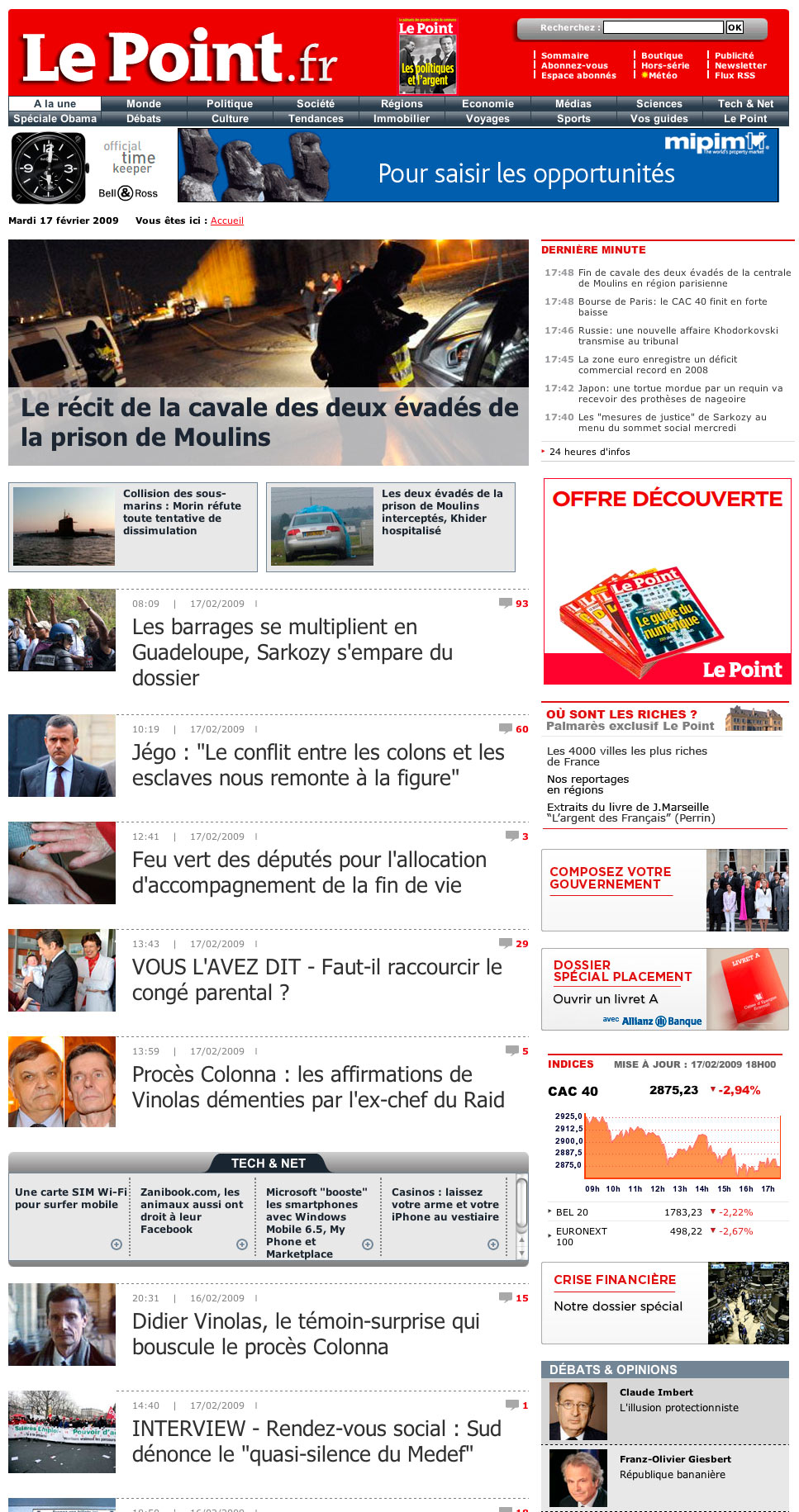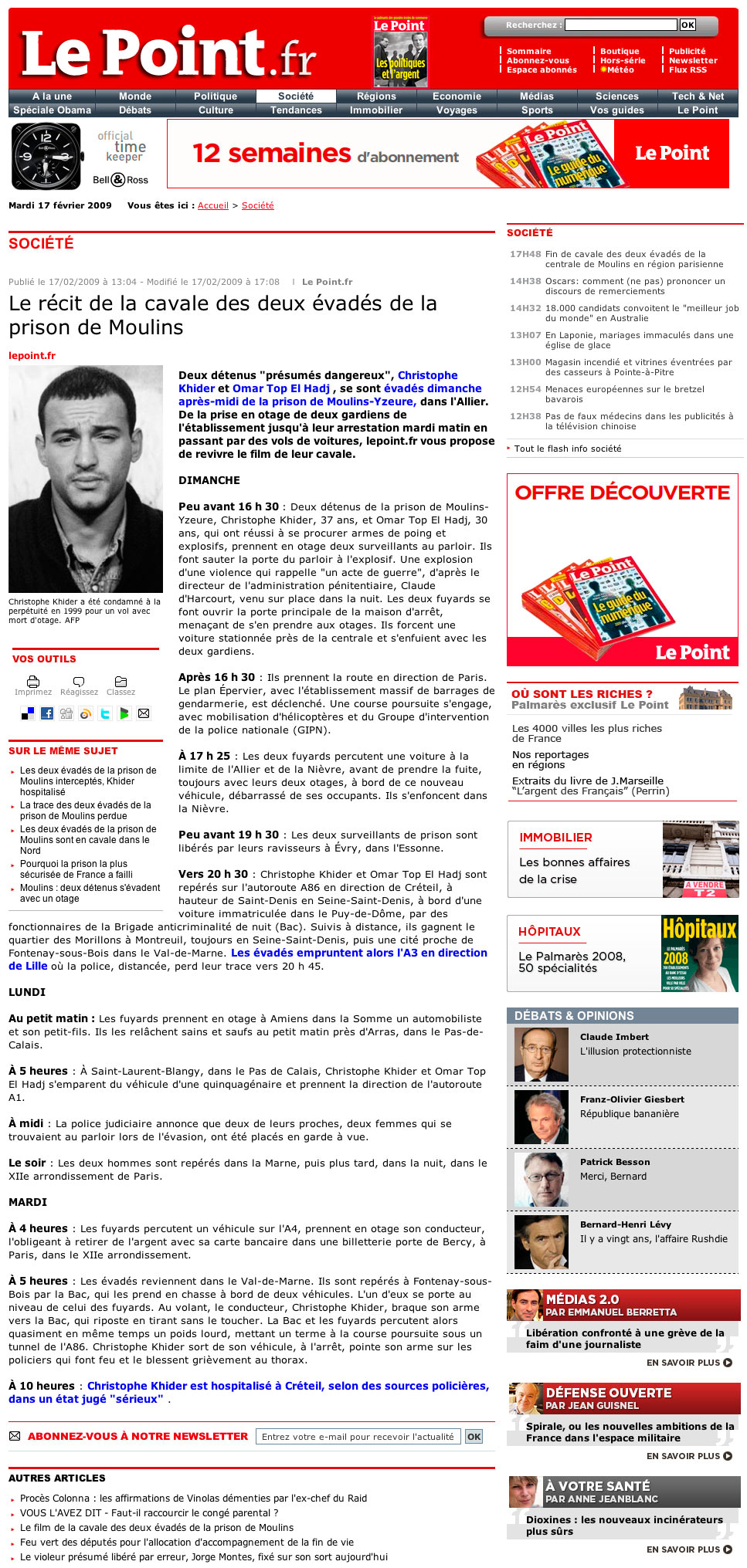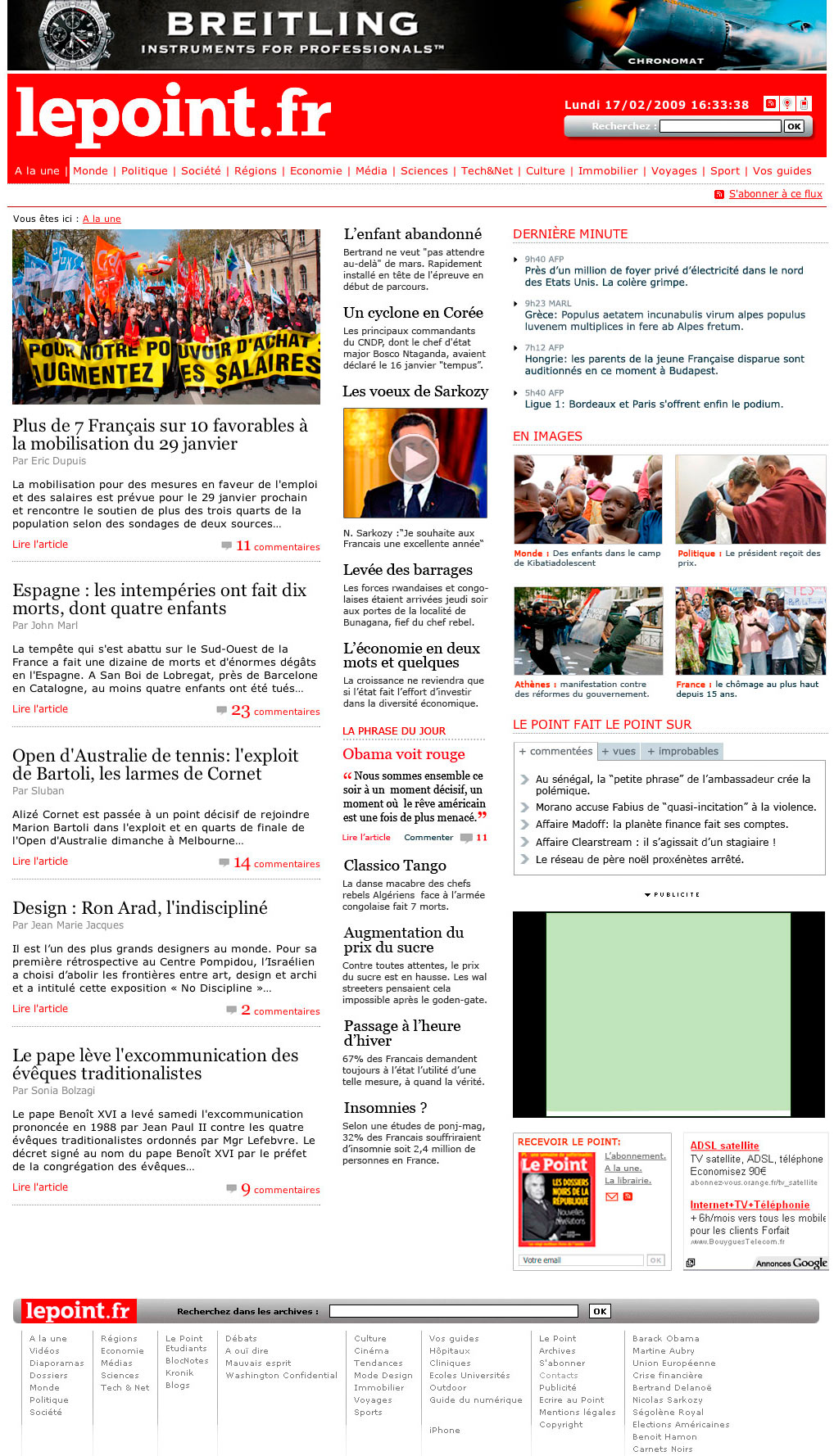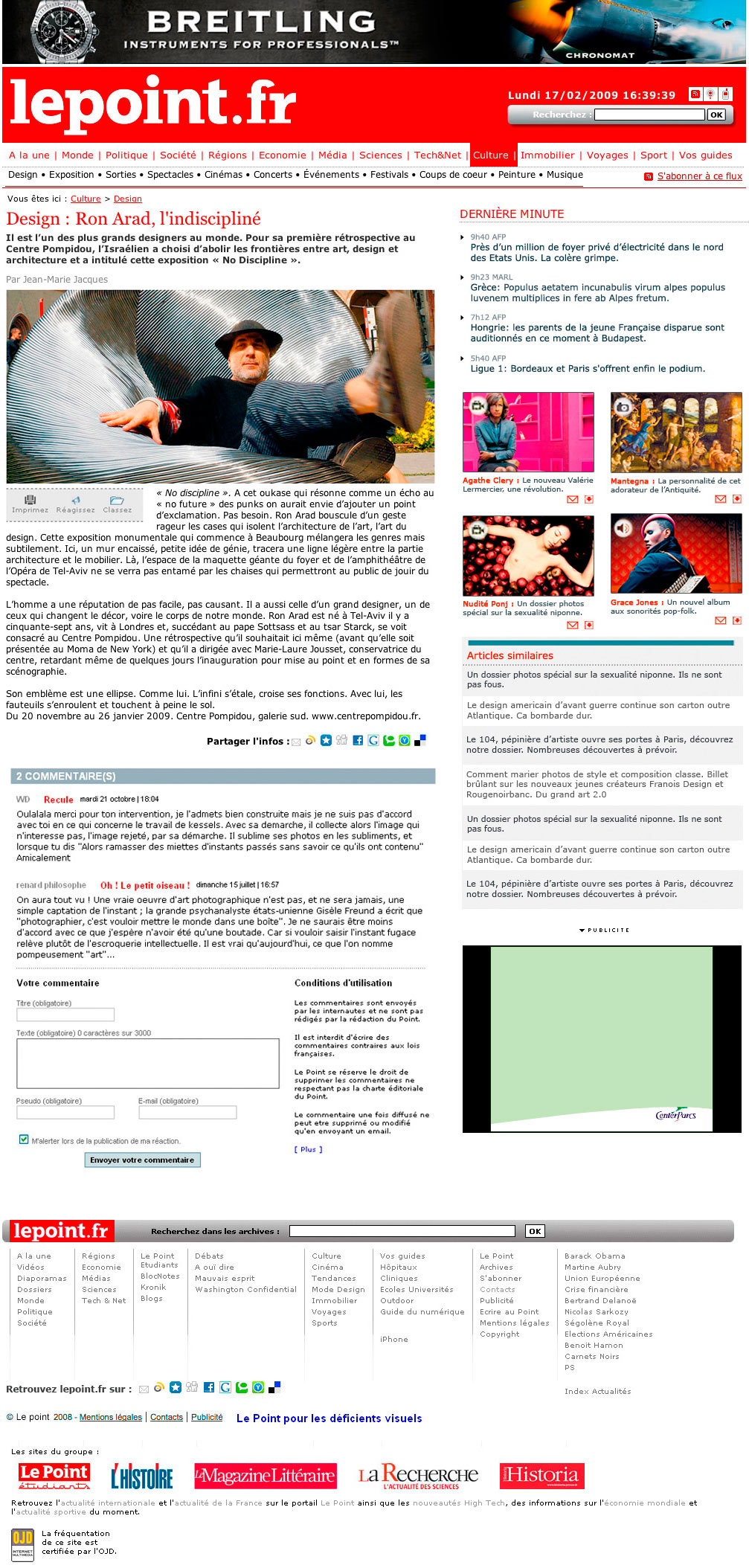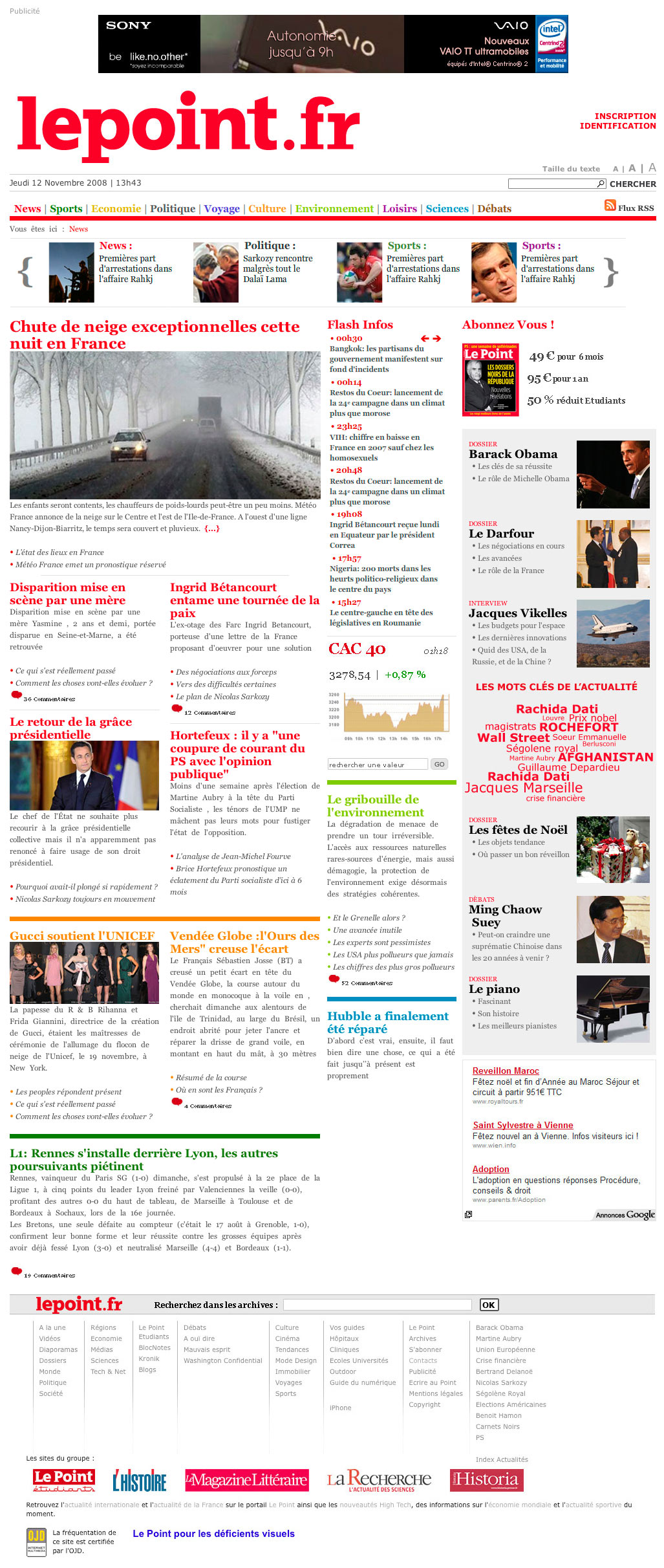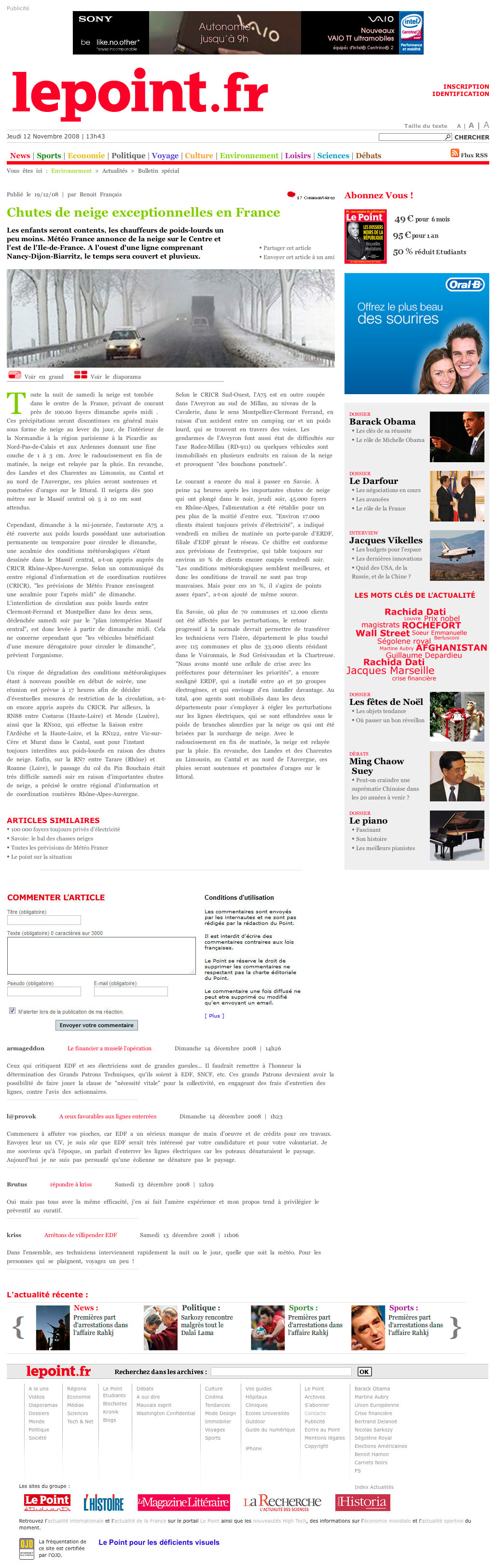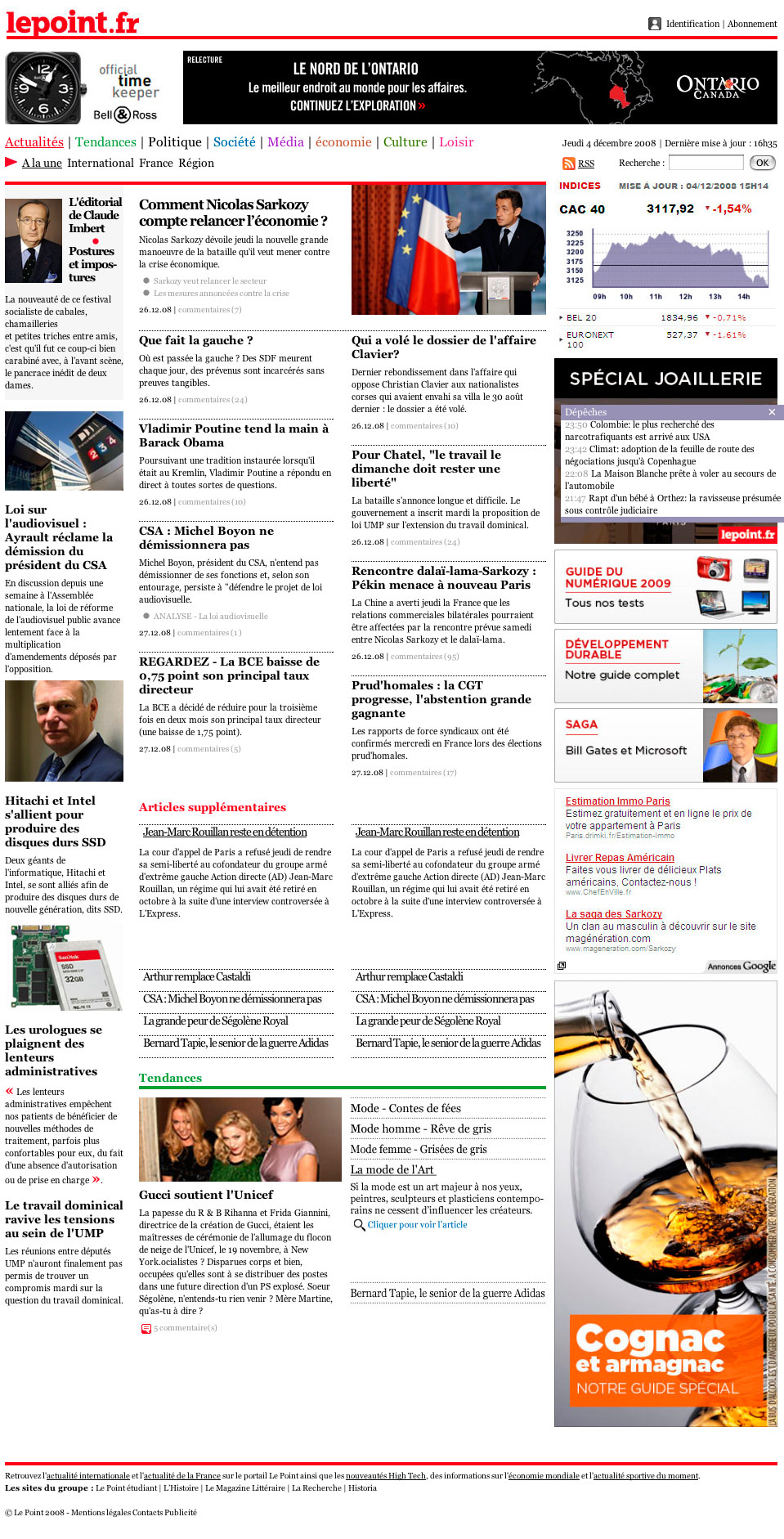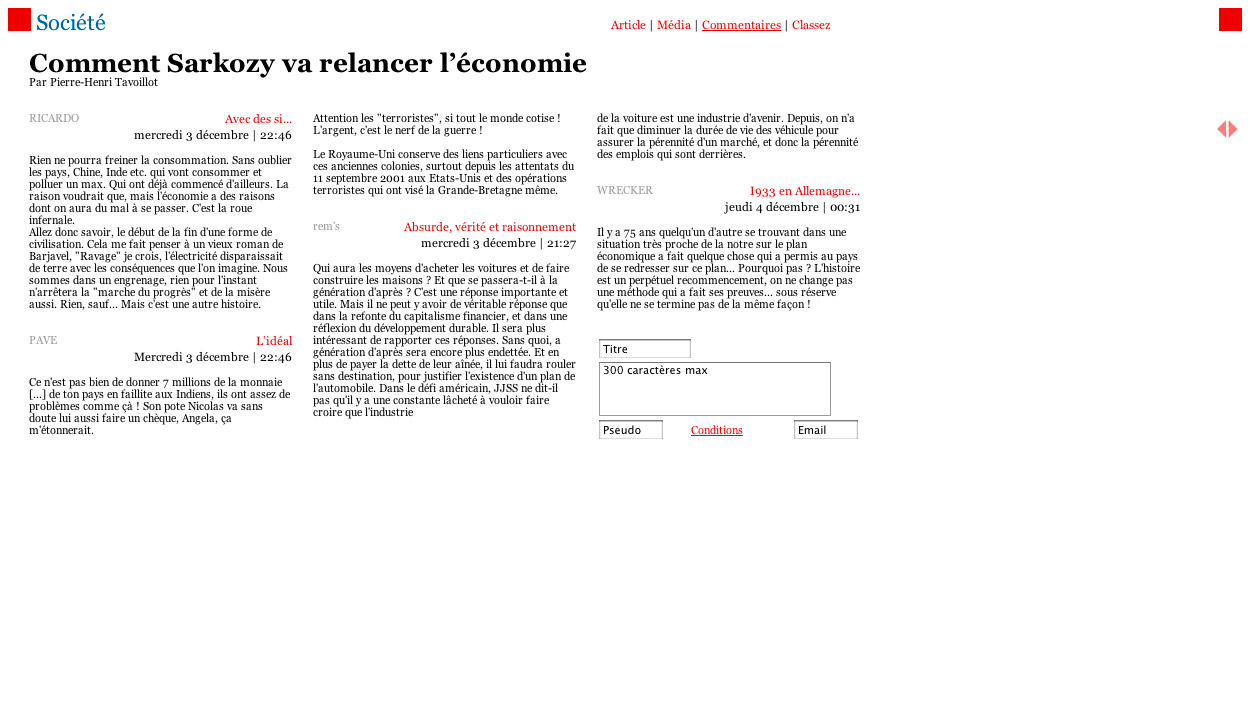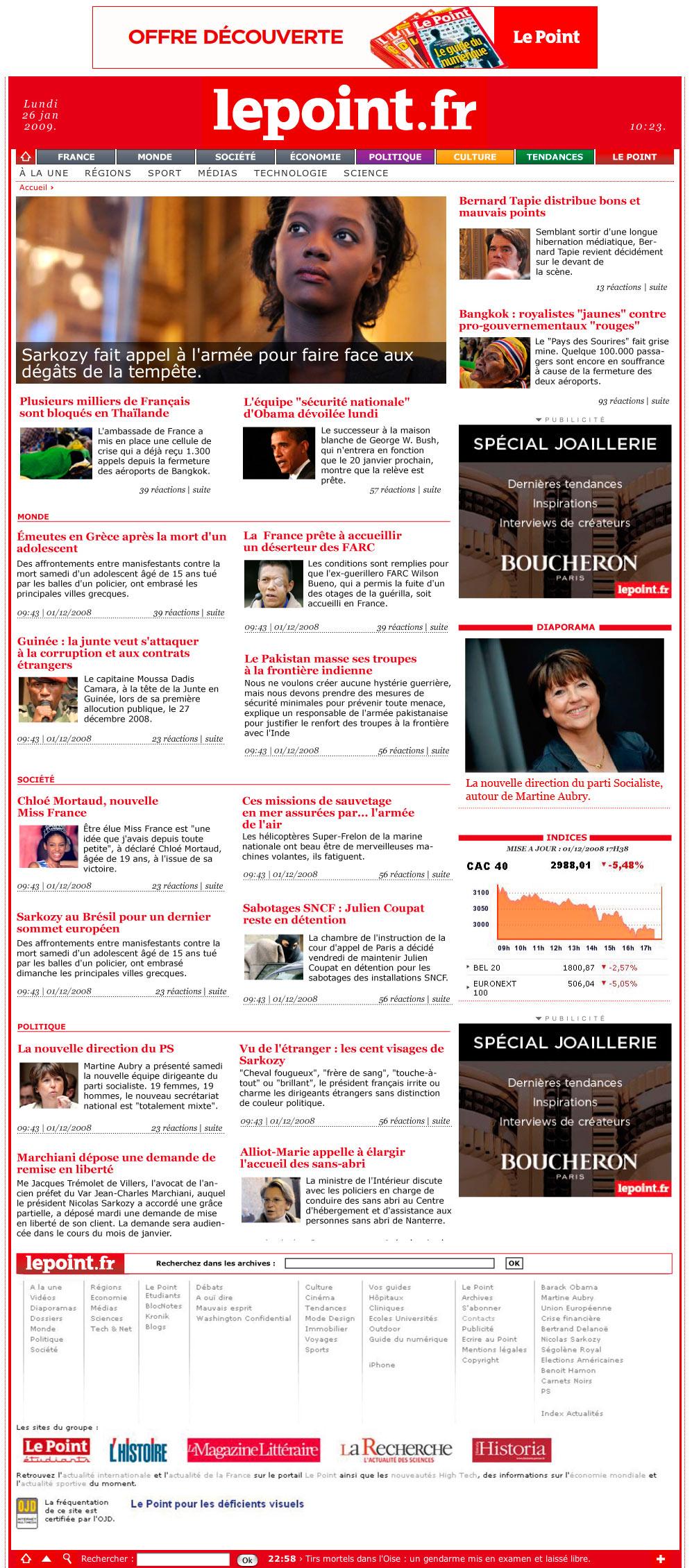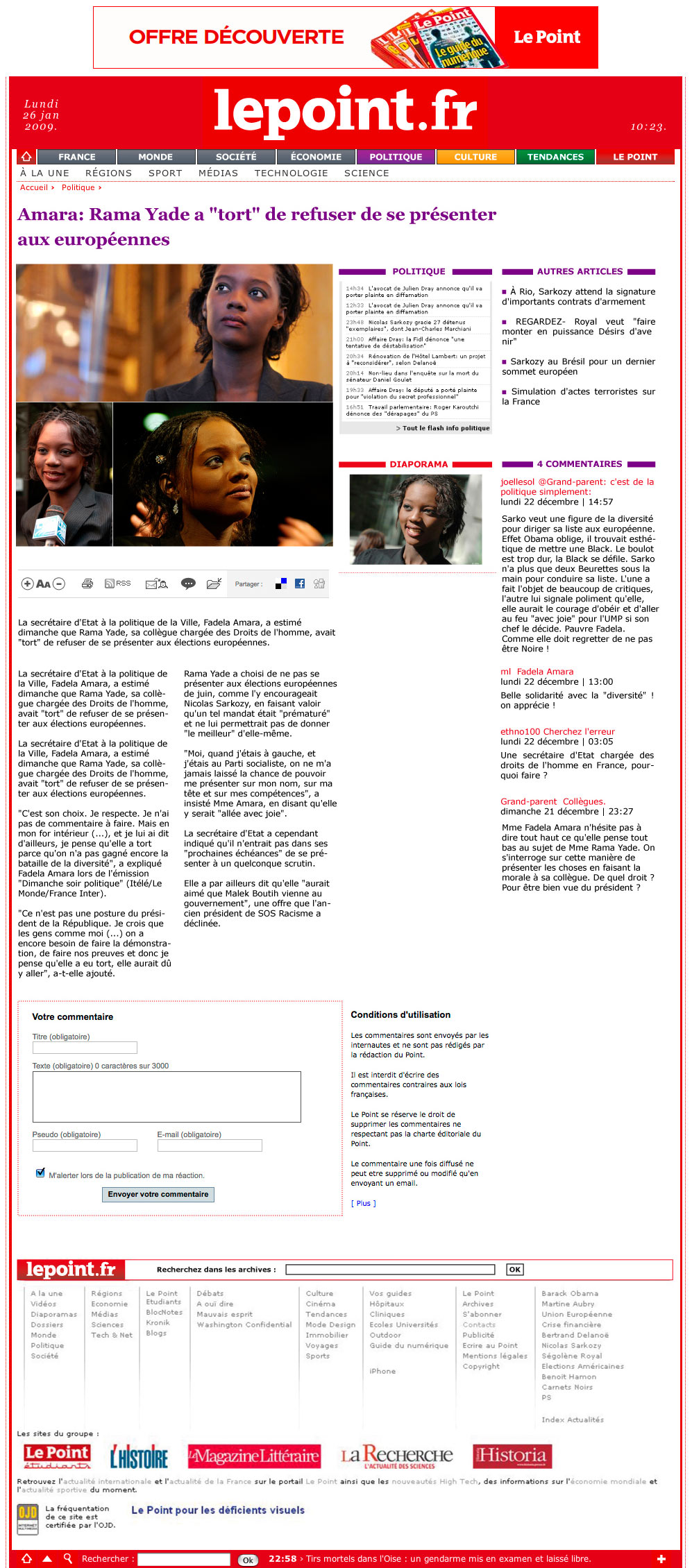
une école de la création numérique…
…qui ne s’attaquerait pas à l’un des exercices les plus nobles et fondamentaux de notre système d’information ne remplirait pas vraiment sa mission. C’est en tous cas, le préambule que j’ai posé après la réunion de brief que nous avons eu avec la Rédaction du Point. C’est de même, pas tout à fait la première fois que j’entraîne mes étudiants à se confronter au design de presse puisqu’en 2005-2006 j’avais déjà abordé la question de leur faire refaire la maquette du Monde (version papier).
Mais pour quelle raison est-ce si difficile?
La presse n’est pas un produit comme un autre. Sa mission, malgré un modèle économique qui l’oblige, comme tout entreprise, à présenter des comptes de résultats positifs chaque année, sa mission donc est d’informer, d’enquêter (d’investiguer), interviewer, rendre compte des crises, de leurs causes et des acteurs de l’information politique, sociale, économique et culturelle sans oublier bien entendu le sport. Tâche noble, si elle en fut. Des générations de journalistes se sont battus pour la liberté d’expression et je ne reprendrai pas ici les débats initiés pas Edwy Plenel en marge des états généraux de la Presse, parce que, ni le lieu ni le moment, mais l’affaire de cette liberté n’est jamais tout à fait acquise. On le sait. Toutefois, parmi les causes de la désaffection du public pour la presse Quot. j’en retiendrai une: La perte d’identité et de la culture de l’information. Le manque de respect des lecteurs donc.
Oh ce n’est pas ici, sur le portail du Monde Interactif que, ceci soit le plus évident. Plutôt même le contraire. Le Monde Interactif est l’un des fleurons de nos journaux en ligne pour avoir compris la nécessaire transversalité d’une information qui va du papier vers le papier en passant par le monde des écrans. Ou l’inverse d’ailleurs. Mais transversalité veut dire continuité.
La presse écrite imprimée a inventé des codes de mise en page et de rythme de lecture. Rompant avec le Livre, elle a découvert la nécessité de mettre en page les articles, et en premier la Une de sorte que l’on favorise en permanence la hiérarchisation de l’information (allant parfois même, jusqu’à exagérer) et la lecture la plus confortable donc la plus rapide. On a donc inventé pour cela des colonnes, et, forcément, des grilles de mises en page.
Vous trouverez dans les articles de design et typo un certain nombre de sujets qui traitent de la lisibilité, des gris typo , de l’interlignage, des contrastes et du noir au blanc et notamment cette évidence physiologique concernant la fatigue rétinienne lorsque obligé de fixer trop longtemps une ligne de texte trop longue. 30 à 55 signes par ligne correspondrait au meilleur confort de lecture. Au delà, nos yeux décrochent de la ligne, sauf, sauf si l’on joue avec l’interlignage en augmentant les blancs entre les lignes. Mais le journal Papier ne pouvait se permettre de tels gaspillages et dès lors on assistait chaque fois à la recherche du meilleur compromis (forme des caractères, chasse, et approches, ainsi et surtout, la hauteur d’œil des polices, qui devaient être les plus grands possibles) pour la lisibilité et l’économie d’espace. Toute contraintes qu’Internet n’a pas besoin de reproduire (il y en a d’autres).
Et pourtant… Je vous parlais des codes, nous aurions pu aussi bien parler de l’ADN de la presse traditionnelle, celle-ci est connue et reconnue par les lecteurs du monde entier. J’ai donc invité bien entendu nos étudiants d’e-artsup, d’aller y voir de plus près (benchmark). Journaux américains en ligne, Anglais, Allemands Espagnols aussi. NewYork Times et Guardian, El País etc. Mais également de se reporter à une étude que j’avais mis en ligne spécialement pour eux ici.
Le brief décrypté par les étudiants…
«Le Point en ligne est selon nous la continuité du magazine papier, créé il y a une trentaine d’années par Claude Imbert, l’homme au col de chemise blanc. Revue plus que magazine d’ailleurs, Le Point s’est toujours efforcé de se situer au dessus des champs de bataille en adoptant la posture de journalistes qui enquêtent et réfléchissent et décryptent les infos pour des lecteurs curieux des non-dits de l’actualité.
Lecteurs sans doute privilégiés, CSP+ et ++ il nous apparaissait nécessaire de retrouver dans le journal en ligne cet ADN fondamental qui traduit l’histoire d’un magazine, d’une presse. Le Point c’est sérieux, et les codes de mises en page actuels, ne nous semblaient pas traduire les fondations de la rédaction. Rédaction qui de plus est, est sincèrement soucieuse de respecter son lectorat. Nous l’avons constaté plusieurs fois au cours de nos réunions préliminaires. Alors sans doute, faute de temps, et d’investissement majeur, l’actuel portail du Point, qui par ailleurs voit son audience augmenter d’année en année, traduit assez mal la passion journalistique que nous avons découvert chez nos interlocuteurs. Un portail en deux colonnes avec un déroulé obligeant les lecteurs à scroller plus qu’il ne faudrait.
Des polices aux dimensions monumentales qui occupent un espace vertical qui augmente encore la nécessité du scrolling et du coup, un manque cruel d’hiérarchisation de l’info qui donne plus l’impression d’un «canon à dépêches AFP» que d’un journal au sérieux si patent. Voilà. Retrouver les principes qui ont fait le succès du magazine, permettre aux lecteurs de l’édition papier à se sentir chez eux en lisant leur quotidien en ligne. De sorte, qu’en essayant de ne pas perdre de lectorat, on récupère celui, original du mag.
Bien sûr on peut nous rétorquer que le portail risque alors de tuer le magazine papier. C’est sans compter la différence essentielle entre les deux. Le mag papier, hebdomadaire, qui prend le temps de construire une pagination et raconte l’histoire des actus en prenant la posture historique qui est le sien, le journal en ligne, au rythme quotidien qui publie les infos, rend compte des dernières nouvelles du monde et n’a pas toujours le temps de prendre le recul nécessaire au décryptage des actualités. Les deux publications ne se marchent pas l’un sur l’autre. Tout au plus, elles risquent de temps à autre de se chevaucher, mais le lectorat traditionnel du magazine, aime lire, aime feuilleter le papier. Nous avons donc pensé qu’il était parfaitement inutile de prendre des précautions qui limiterait la qualité graphique du journal en ligne.»